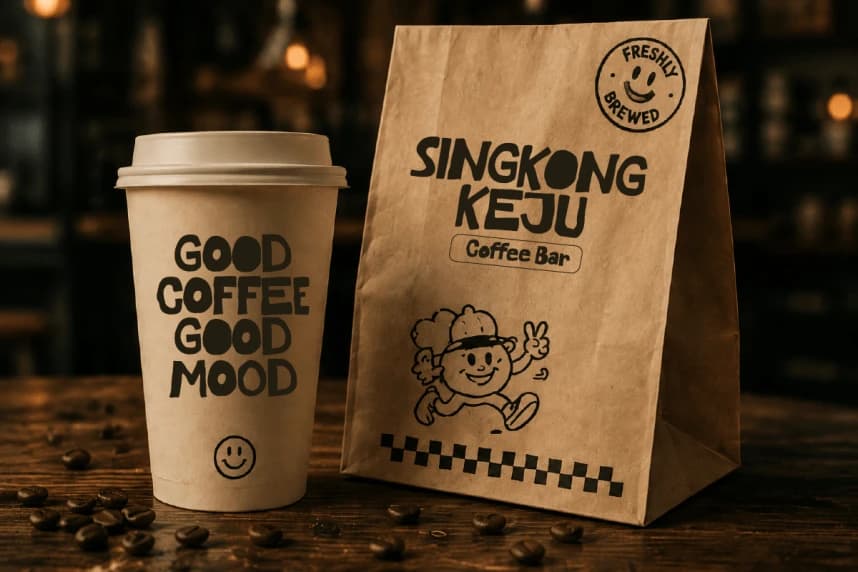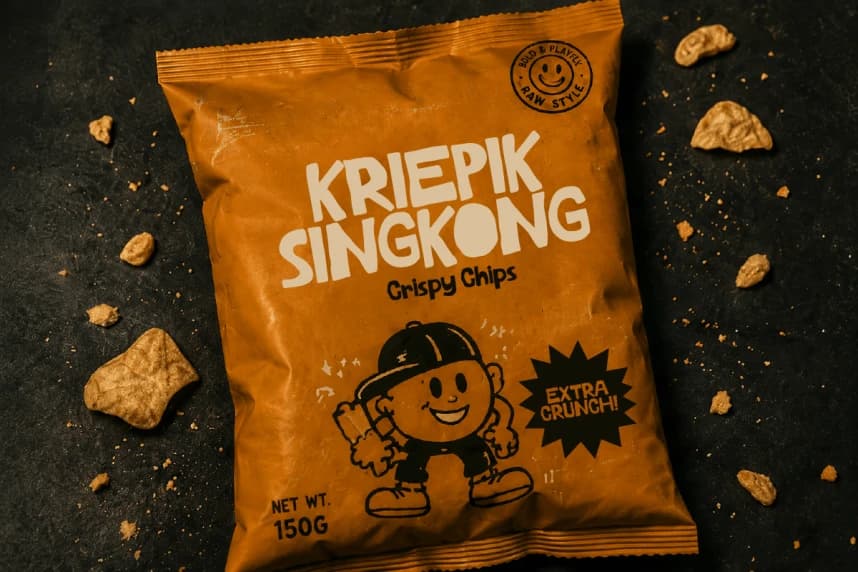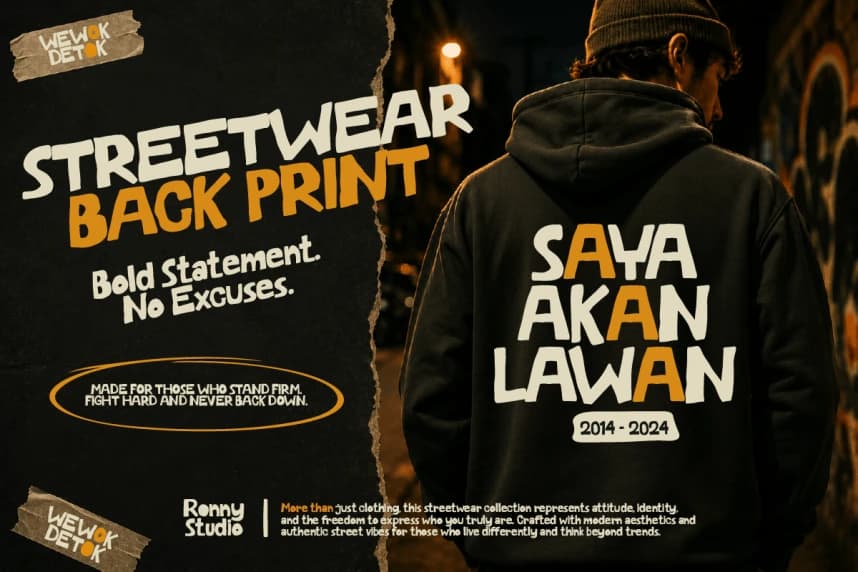
Wewok Detok – Kalın Eğlenceli Gösterim Yazı Tipi
Wewok Detok – Bold Playful Display Font, eğlenceli ve cesur bir gösterim yazı tipidir; el çizimi oyuncu karakterlerle anında dikkati çeker. Ambalajlar, posterler, markalaşma, sosyal medya, logolar, başlıklar ve benzersiz ve enerjik bir görünüm isteyen yaratıcı projeler için mükemmeldir.
Wewok Detok – Bold Playful Display Font eğlenceli ve cesur bir gösterim yazı tipidir; el çizimi karakterlerle anında dikkat çeker. Ambalajlar, posterler, markalaşma, sosyal medya, logolar, başlıklar ve benzersiz ve enerjik bir görünüm arayan yaratıcı projeler için mükemmeldir.